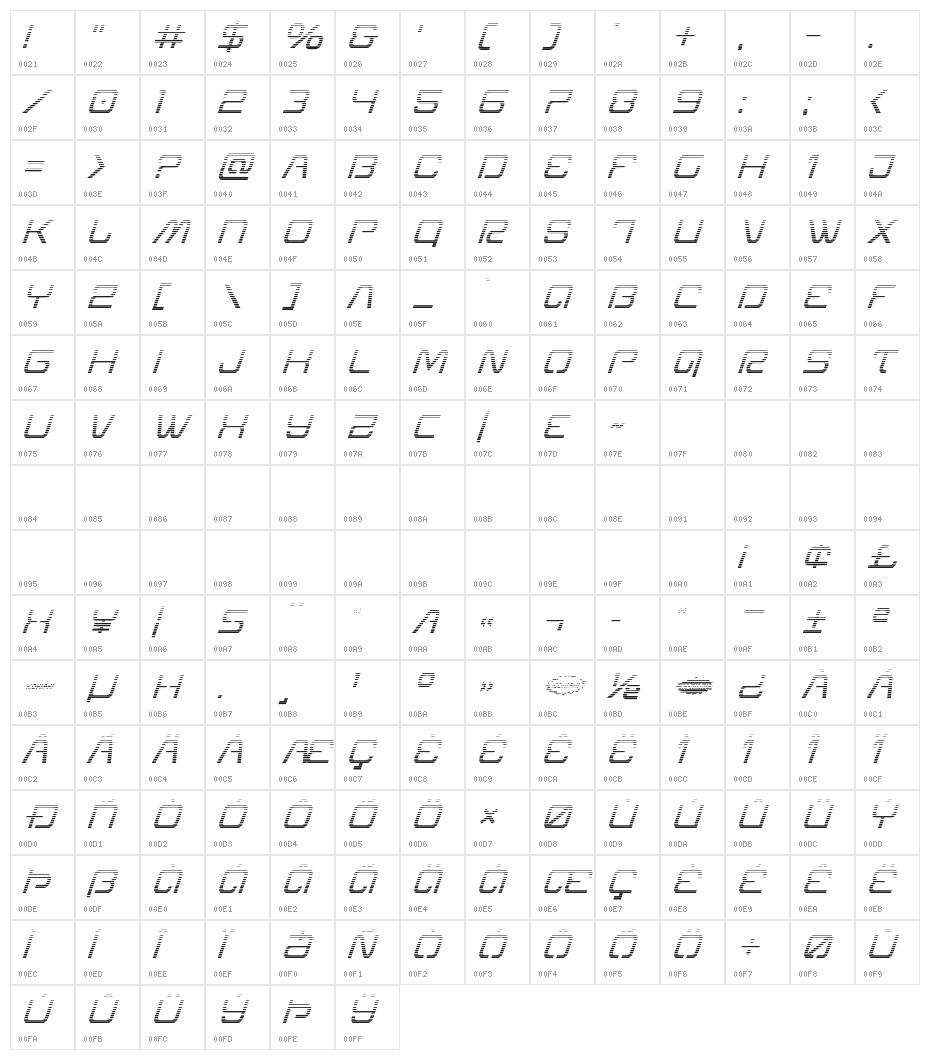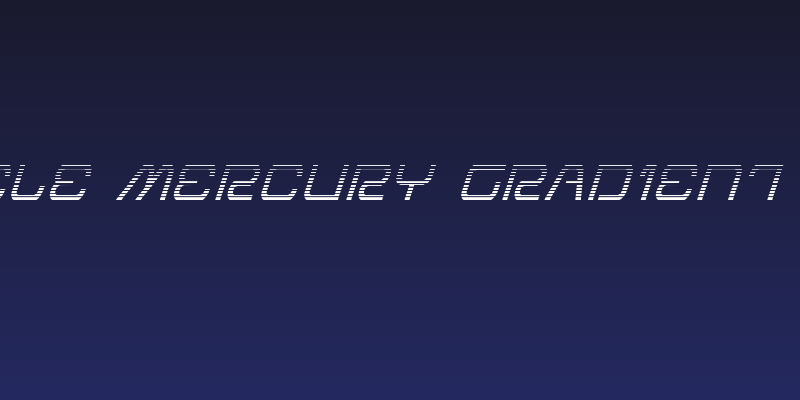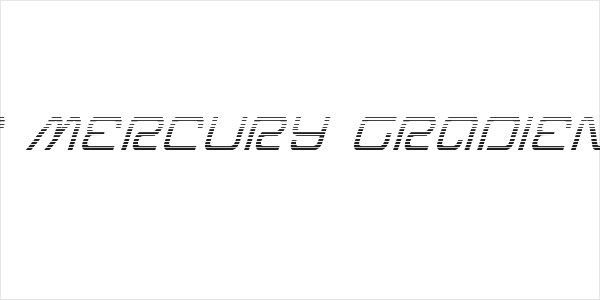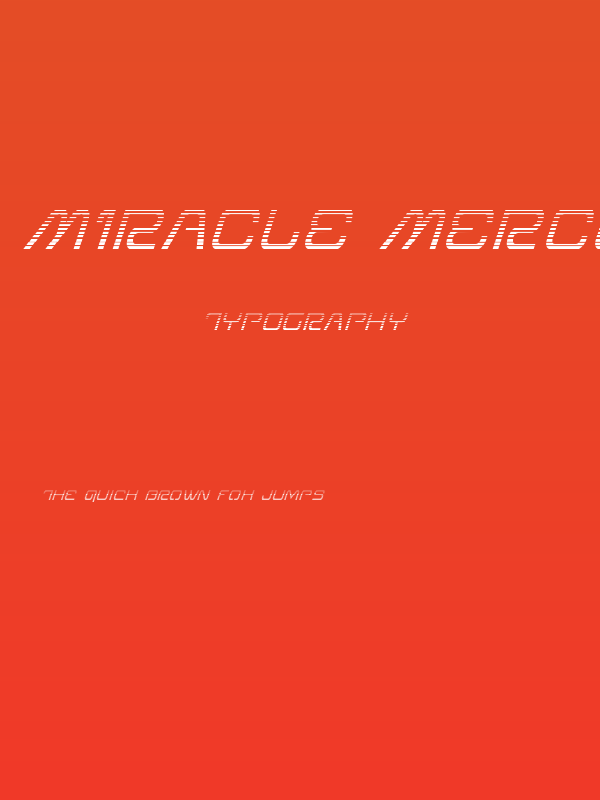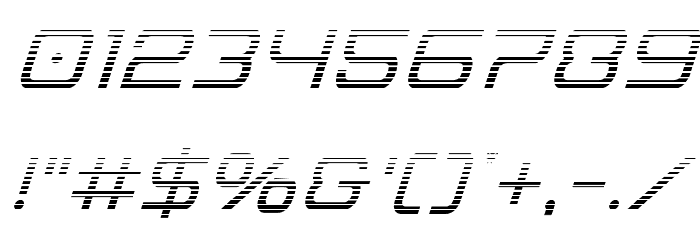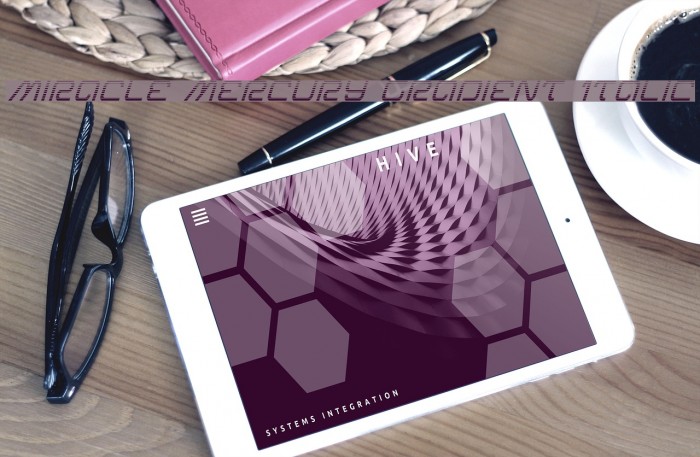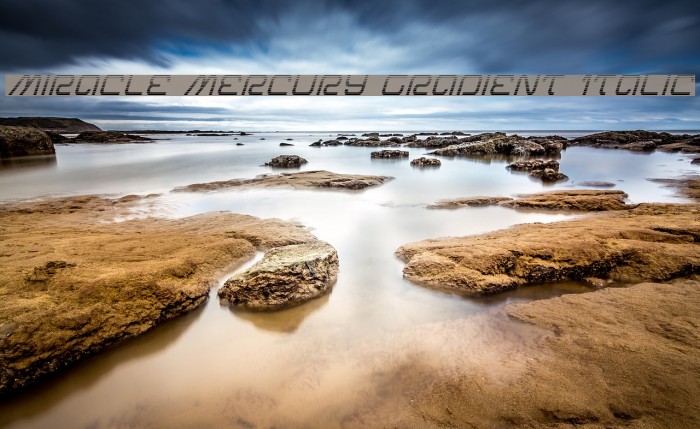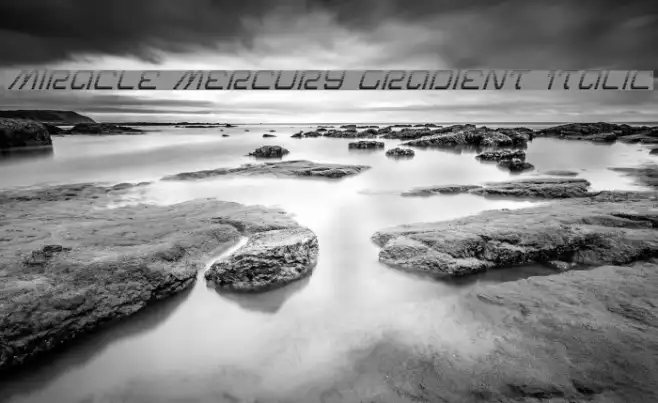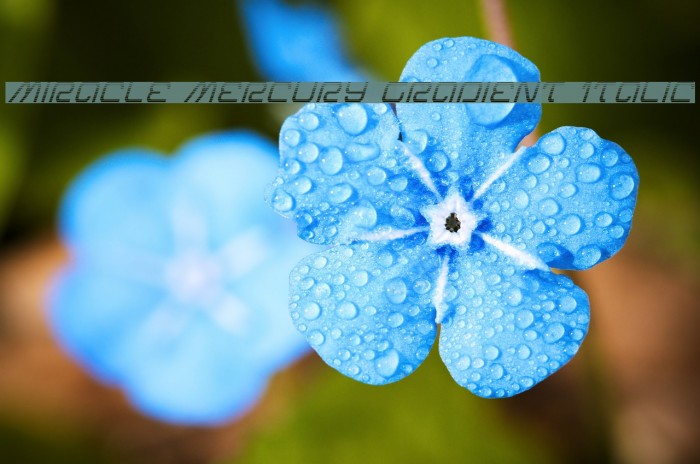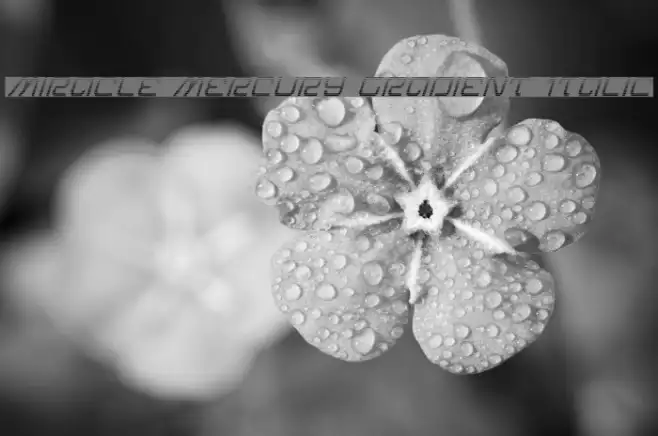
Miracle Mercury Gradient Italic Font
✎ Futuristic
| Kategorien | Futuristic |
| Anwendungsfall | Logos, Headlines, Posters |
| Vorgeschlagene Projekte | Ideal for technology branding, sci-fi movie posters, video game titles, and futuristic event invitations. |